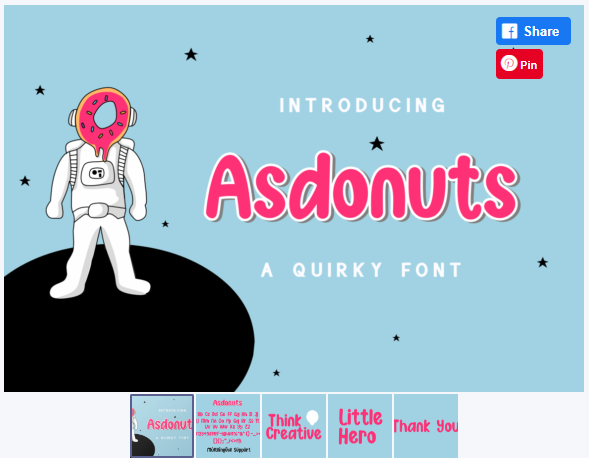
Asdonuts - это шрифт с милой и уникальной особенностью. Этот шрифт забавный, поэтому вы можете выбирать и комбинировать прописные и строчные буквы, чтобы получить идеальную комбинацию.